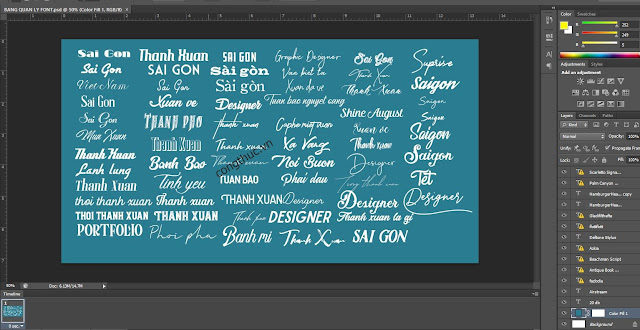
138 Font Thời Bao Cấp Xưa Cũ Dành Cho Bảng Hiệu Xưa
Nhiều anh em design thiết kế bảng hiệu, poster, banner website, facebook, quảng cáo... gửi mail cho diễn đàn, mong muốn có được trọn bộ font thời bao cấp xưa cũ dành cho bảng hiệu xưa.
Đôi nét về bộ font mang giá trị xưa cũ Tác giả của bộ font "mang giá trị xưa cũ” luôn cảm thấy hứng thú với những biển hiệu vẽ tay, như trending “Vịt lộn vịt dữa cút lộn” khiến cộng đồng mạng dậy sóng. Trong khi đó, các biển hiệu ngày nay được làm theo dạng công nghiệp, dùng font chữ Việt hóa lỗi thời, bỏ dấu đơn điệu, mất đi những nét đẹp truyền thống giống như các bảng hiệu thời xưa, vốn đậm chất nghệ thuật. >>> Xem thêm bộ sưu tập font chữ viết tay vintage retro việt hóa Hồi ức Bộ font giá trị xưa giá 400k Bộ Font “Giá Trị Xưa Cũ” của iCiel được tác giả chọn lọc kỹ, Việt hóa theo phong cách bỏ dấu xưa, rất phù hợp với các loại poster, bảng biển quảng cáo đậm chất hoài cổ. Font chữ “Giatrixuacu” độc quyền của iCiel được thiết kế trong gần 2 tháng, từ nghiên cứu cách bỏ dấu cho đến chăm chút từng đường nét. Bộ font “138 font thời bao cấp - giá trị xưa cũ” bao gồm: - font chữ dành cho tựa đề
- Font chữ serif dành cho body text.
- Các font này đều có tính năng smallcaps tự động.
Kiểu chữ: Serif, Sans, Modern, Transitional, Oldstyle, Retro. Tính cách: Cổ điển, Handmade, Condensed Số fonts: 15. Các anh em có thể dễ dàng biến mọi font chữ thành có hiệu ứng handmade, có texture bụi, xưa cũ. Phù hợp với bộ font này. Tất cả các font chữ đều có tiền tố iCielBC ở đầu để dễ phân biệt. Bản demo font Giá Trị Xưa Cũ Đôi điều về bản quyền. Đây là bộ font chữ do một nữ chủ shop (iCiel) tại Hà Nội, từ tay thiết kế dựa trên nguồn cảm hứng từ những bảng hiệu vẽ tay thời bao cấp. Vì vậy, các anh em tải về về dùng cá nhân, chứ với các hoạt động thương mại. Về Tác Giả của Font bao cấp